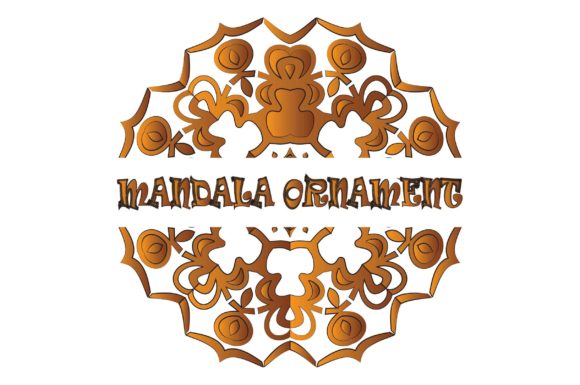
Mandala
適切なデザイン要素を見つけるのは難しい場合がありますが、Mandalaは作品を即座に引き立てる優れたコレクションを提供します。
精密に作られたMandalaは、クリーンなベクター、滑らかなタイポグラフィ、そして安心のための商用ライセンスを提供します。
POD(オンデマンド印刷)製品、結婚式の招待状、またはソーシャルメディアのグラフィックを作成している場合でも、Mandalaは理想的です。